今回は、今野真二著の『漢字とカタカナとひらがな-日本語表記の歴史-』をご紹介します。
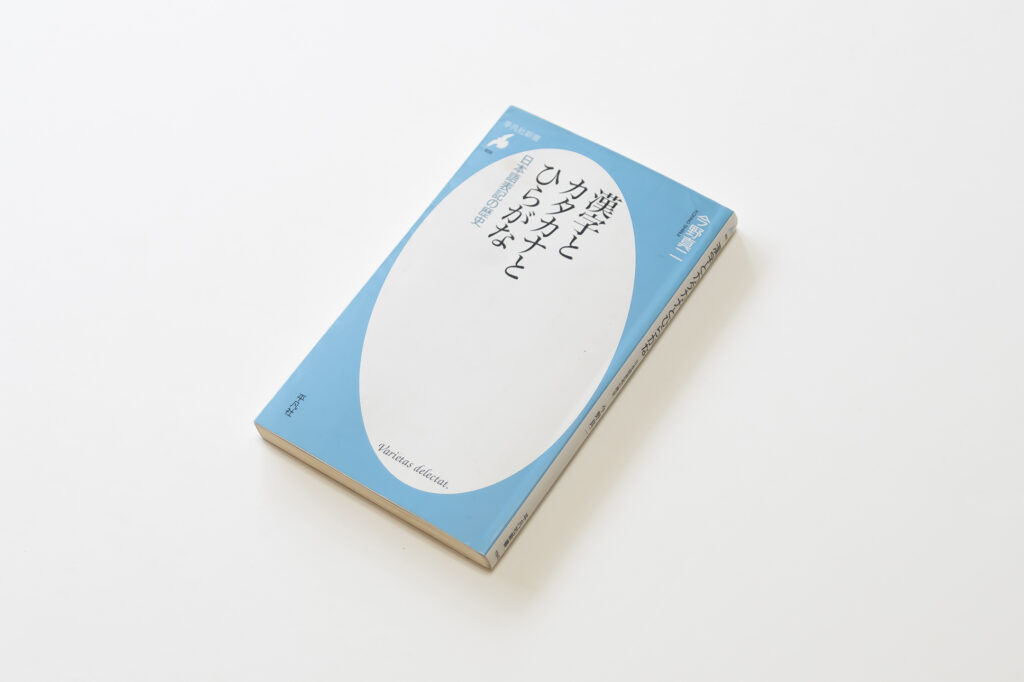
日本語表記が現代の漢字仮名交じりに至るまでの紆余曲折を、様々な歴史資料から読み解いていく内容です。古墳時代の銅鏡に始まり『古事記』『万葉集』『平家物語』など誰もが知るような資料も扱われ、日本語学者である著者がそれらの表記をじっくりと細かく観察していきます。
私が特に興味が惹かれたのは書体に注目した分析で、テキスト内容・文字種・書体の密接な関係が解説されていました。以前このブログでは「漢字・ひらがな・カタカナの組版」と題し現代の日本語表記に触れましたが、仮名の成り立ちについてもっと知りたい、過去の日本語はどんな表記をしていたの?と気になる方にオススメしたい一冊です。